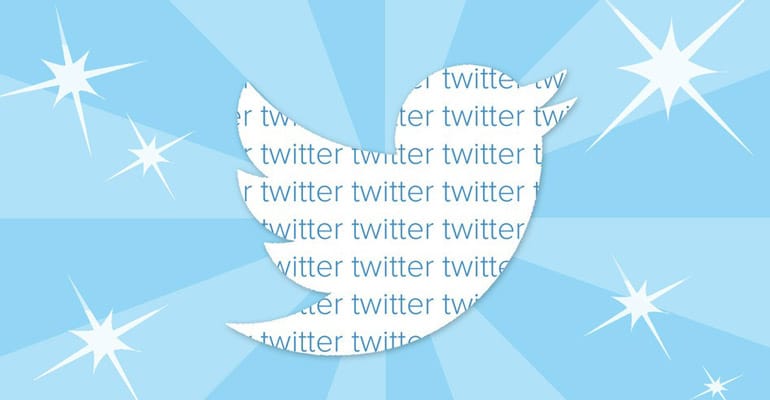
Twitter’ın Yazı Tipi Değişti
Popüler sosyal medya sitesi Twitter’dan bugün içerisinde büyük bir güncelleme haberi elimize ulaştı. Twitter.com sitesine girenlerin hemen fark edeceği üzere Twitter uzun zamandır kullandığı Helvetica Neue yazı tipini Gotham yazı tipi ile değiştirdi.
Uzun süredir Gotham adlı yazı karakterinin yeni Helvetica olabileceği konuşulmaktaydı fakat bizim görüşümüz bu yazı karakterinin Twitter’ın havasını kötü yönde değiştirdiğine dair.
Starting today, we're rolling out a new font on http://t.co/zDdcbPwclU, moving from Helvetica Neue to Gotham.
Helvetica Neue’nin okunaklı ve ferah yapısı Gotham yazı tipi ile küçültülmüş ve daraltılmış durumda. Belki henüz gözümüz tam olarak yeni yazı tipine alışmadığı için bu şekilde düşünüyor olabiliriz fakat çok daha iyi alternatifler varken bu yazı tipinin seçilmesi gerçekten de ilginç.